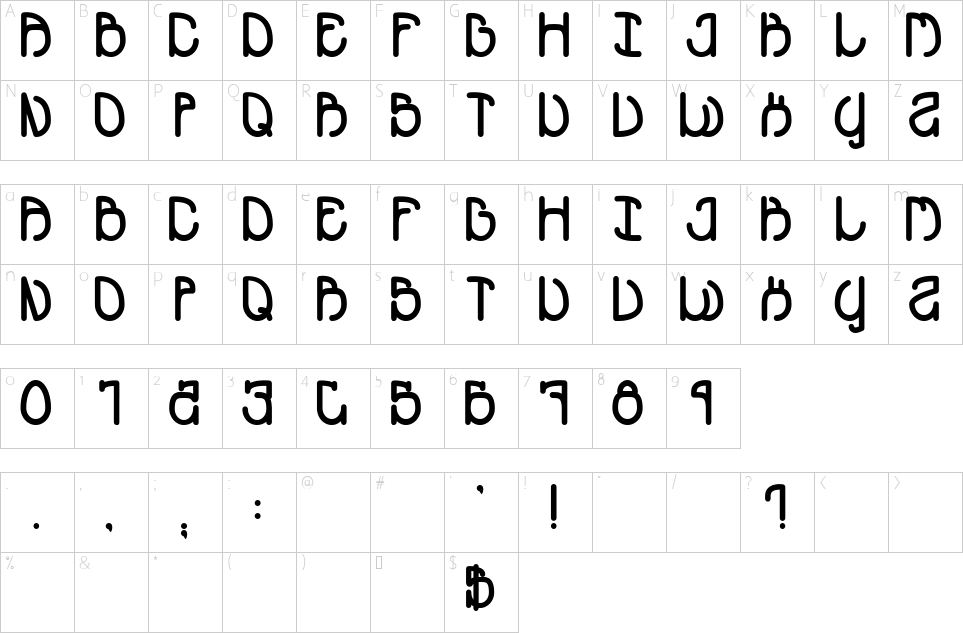
Descubra Metropolis, uma fonte de caracteres minimalista e elegante disponível de graça. Desenvolvida pelo designer Qkila, esta fonte é uma escolha ideal para designers e profissionais que buscam uma opção moderna e não intrusiva. Metropolis foi projetada para oferecer uma experiência confortável e eficiente em dispositivos Windows e Mac. Se você busca uma fonte clara e moderna para aplicativos, sites ou impressões, Metropolis é uma excelente opção. Este é um exemplo claro do que se espera de um bom recurso gráfico de fontes gratuitas, disponível para todos os usuários. Atualmente, Metropolis já foi baixada mais de 2.251 vezes, indicando seu valor e popularidade. Seja você um estudante, um freelancer ou um profissional de design, Metropolis oferece o design profissional que você precisa.